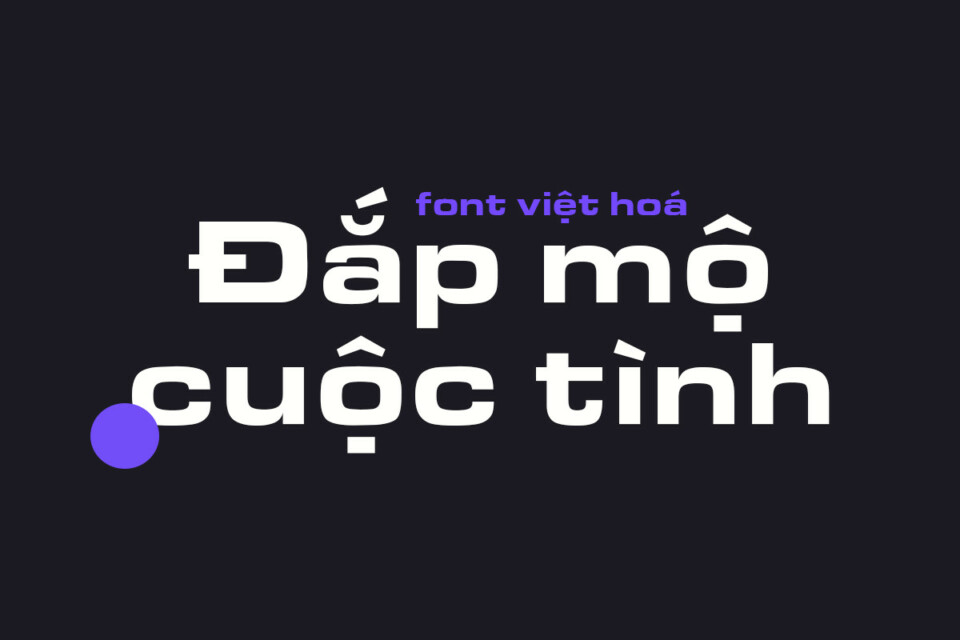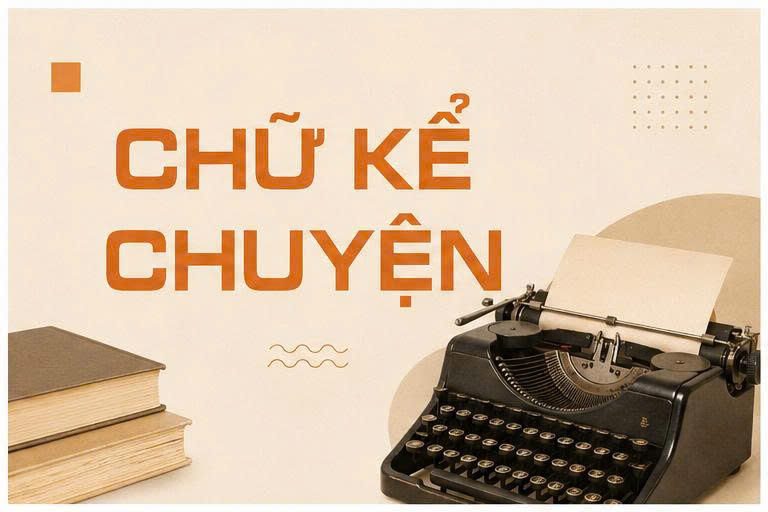
Font Eurostile Việt hóa là bộ phông chữ thuộc dòng Geometric Sans-serif kinh điển do nhà thiết kế Aldo Novarese sáng tạo tại Turin (Ý) vào năm 1962, nổi tiếng với cấu trúc hình học bo vuông độc đáo mô phỏng khung màn hình vô tuyến truyền hình và bảng điều khiển tàu vũ trụ thập niên 1960. BCD House chia sẻ kho tài nguyên này nhằm hỗ trợ cộng đồng làm nghề tiếp cận nguồn tư liệu sáng tạo phong phú mà không gặp trở ngại về lỗi hiển thị tiếng Việt.
Khung hình quả trứng vuông superellipse và khí chất viễn tưởng của font Eurostile Việt hóa
Điểm cuốn hút của font Eurostile Việt hóa nằm ở tỷ lệ hình học “Superellipse”, nơi các cạnh thẳng đứng và nằm ngang kết hợp mượt mà cùng các góc lượn mềm mại, mang lại cảm giác cơ khí chính xác nhưng không hề thô ráp. Khác với các dòng phông tròn trịa thông thường, Eurostile sở hữu cấu trúc nén lùn và kéo giãn bề ngang có chủ đích, tạo nên một bệ đỡ thị giác kiên cố như những khối module lắp ghép chịu lực.
Sự ổn định về mặt thị giác của dòng font này giúp truyền tải thông điệp về tính kỷ luật, sự hiện đại và tinh thần tiên phong khám phá không gian. Khi xuất hiện trên các bề mặt vật liệu kiến trúc thế hệ mới như tấm nhôm xước alu, vách kính phản quang đen mờ, khung thép hộp định hình hay dải đèn LED âm tường trong các căn nhà container thông minh, Eurostile tạo nên sự hòa quyện thẩm mỹ tương lai đầy thuyết phục.
| Phân loại phong cách | Geometric Sans-serif / Superellipse / Mid-century Sci-Fi |
| Các biến thể tiêu biểu | Regular, Bold, Extended, Bold Extended |
| Mục đích phù hợp | Biển tên showroom công nghệ, bản vẽ CAD, logo xe hơi |
Tư vấn từ chuyên viên: Eurostile sở hữu chiều ngang chữ rất rộng ở các biến thể mở rộng. Để bản thiết kế đạt hiệu quả thẩm mỹ tốt, bạn nên sử dụng biến thể font chữ Eurostile Bold Extended cho các tiêu đề chính, tên công trình hoặc mã hiệu kỹ thuật ở kích thước lớn.
03 Ứng dụng font chữ Eurostile Bold Extended vào công trình thực tế
Nhờ vẻ ngoài khỏe khoắn và tính chính xác cao, bộ phông chữ này mang lại giá trị thực tế lớn trong khâu tạo điểm nhấn cho các công trình hiện đại:
- Biển hiệu mặt tiền cho Showroom Ô tô và Công nghệ Container: Những khối chữ mở rộng của font chữ Eurostile Bold Extended rất ăn ý khi gia công chữ nổi bằng inox xước hoặc alu gắn đèn LED hắt chân, mang lại diện mạo đanh thép và phong thái tương lai thu hút khách tham quan.
- Hệ thống biển chỉ dẫn Trung tâm Dữ liệu và Phòng Lab Thông minh: Phông chữ này khi in trên các tấm kim loại sơn tĩnh điện xám khói hoặc dán decal kính sẽ giúp không gian làm việc của nhà lắp ghép toát lên chất kỷ luật, tạo sự thuận tiện cho kỹ sư khi định vị khu vực.
- Bìa hồ sơ giải pháp kiến trúc viễn tưởng: Sử dụng font Eurostile Việt hóa cho tên dự án và tiêu đề các chương mục giúp tập hồ sơ toát lên vẻ ngoài của một công trình đón đầu kỷ nguyên số, tạo niềm tin lớn với các chủ đầu tư.
03 Lưu ý bố cục font Eurostile duy trì tính dứt khoát và hiện đại
Để khai thác hiệu quả vẻ đẹp của dòng font bo vuông công nghiệp này mà không gây cảm giác chật chội cho bản vẽ, người thiết kế nên lưu tâm một số kinh nghiệm sau:
- Kéo giãn khoảng cách dòng: Do cấu trúc chữ có xu hướng bè ngang rộng, bạn nên thiết lập khoảng cách dòng thoáng đãng (khoảng 1.4 – 1.5 lần cỡ chữ) để các dòng chữ không bị đè nén lên nhau, giữ được nhịp thở hiện đại cho trang in.
- Tránh sử dụng cho văn bản dài: Độ đậm nét cao và chiều ngang lớn của biến thể Extended không phù hợp cho các đoạn văn bản giải thích kỹ thuật dài. Hãy giới hạn sử dụng cho các cụm từ ngắn từ 2 đến 4 từ để tạo điểm nhấn thị giác tập trung.
- Lựa chọn gam màu lạnh kỹ thuật số: Eurostile phát huy hiệu quả thị giác cao khi phối cùng các tông màu mang sắc thái công nghệ như xám titan, xanh cyber, trắng tuyền hoặc cam điện tử trên nền tối mờ, làm nổi bật đường nét vuông vức của bộ chữ.